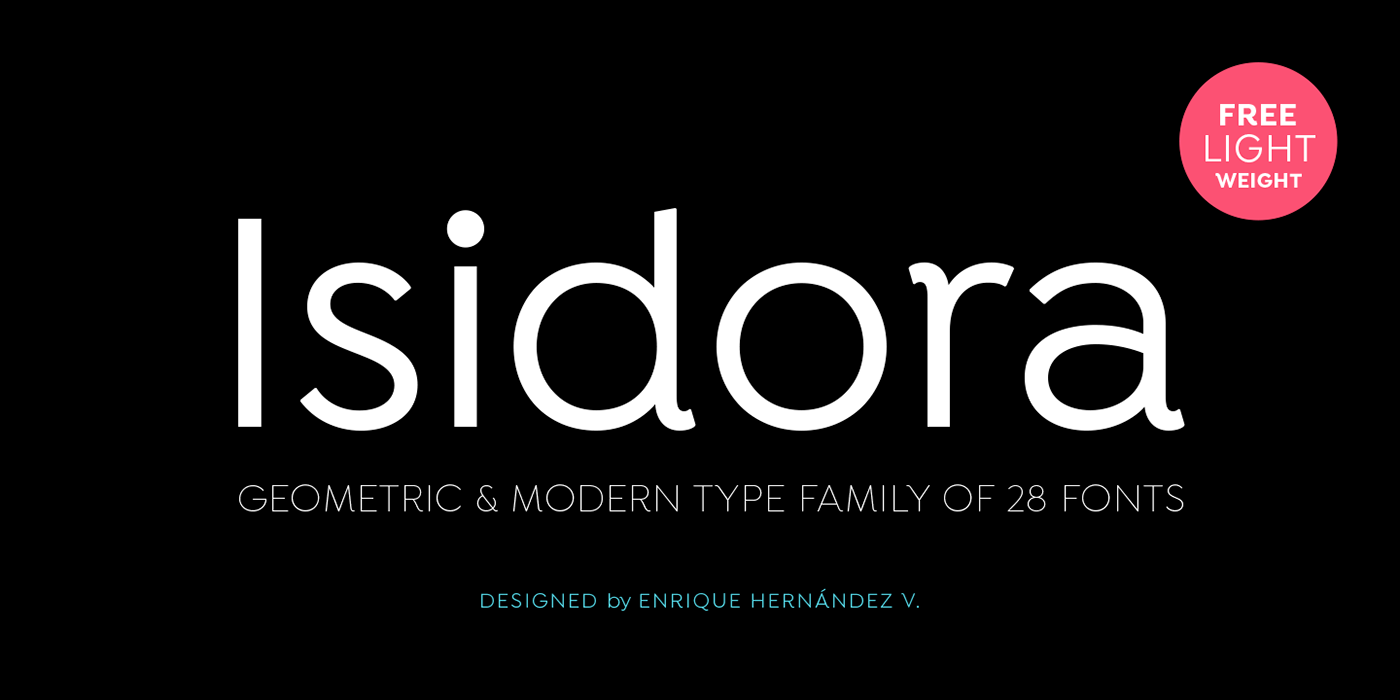
A Isidora Font Family é uma tipografia geométrica moderna desenvolvida por Hamilton, designer brasileiro. Esta família de fontes está inspirada nos modelos clássicos do início do século 21, mas mantém um toque contemporâneo e funcional. O seu formato rígido e lógico consegue manter uma estrutura forte e coerente, embora sua terminação redonda e as cortas diagonal dêem ao texto um aspecto mais amigável e expressivo. Sua aparência é tanto alegre quanto sofisticada, tornando-a perfeita para aplicações que variam desde gráficos de jornal até materiais digitais atuais. A Isidora é uma escolha inteligente para aqueles que buscam um equilíbrio entre estética e funcionalidade em sua próxima projeto visual.